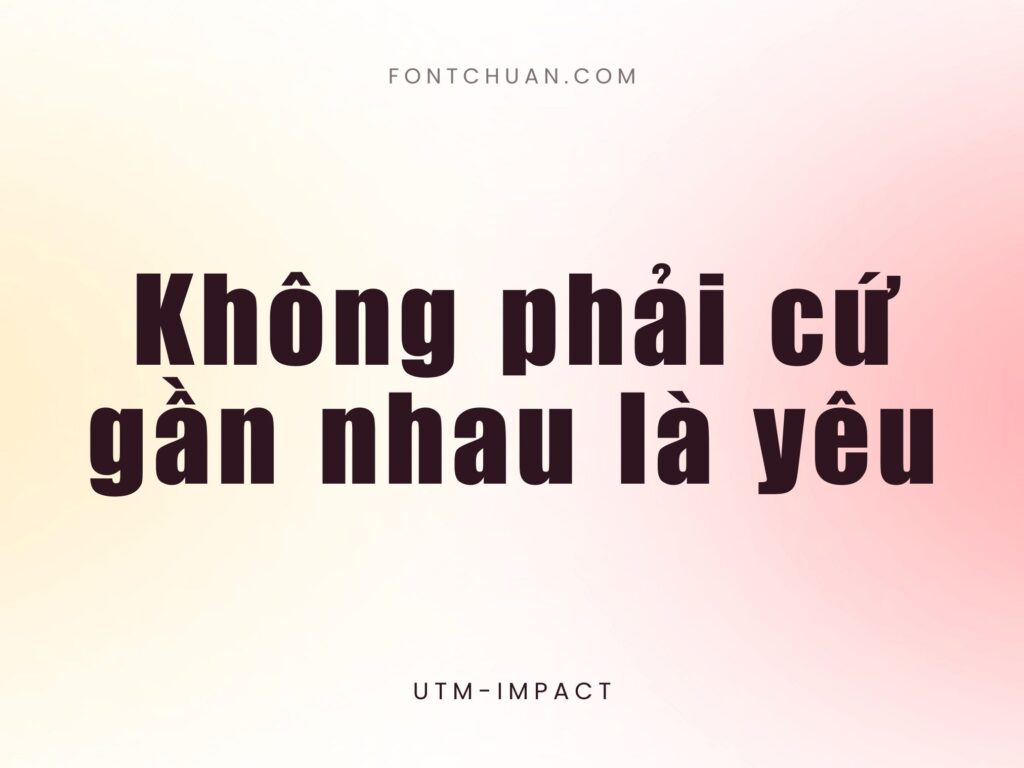
UTM Impact là phiên bản Việt hóa của font chữ Impact, một kiểu chữ sans-serif được thiết kế bởi Geoffrey Lee và phát hành bởi nhà in Stephenson Blake vào năm 1965. Font này nổi bật với các ký tự có đường nét dày, khoảng cách giữa các chữ cái hẹp và chiều cao x lớn, tạo cảm giác mạnh mẽ và thu hút. Phiên bản Việt hóa đã được thực hiện bởi Michael Đinh Kiên, hỗ trợ đầy đủ tiếng Việt cùng hơn 100 ngôn ngữ khác. Đây là một trong những font được cộng đồng thiết kế sưu tầm và chọn lọc nhằm đáp ứng nhu cầu đa dạng trong thiết kế.
UTM Impact có cấu trúc chữ với các nét đậm và khoảng cách hẹp giữa các ký tự, tạo nên sự nổi bật và dễ đọc. Font này phù hợp cho các ứng dụng như thiết kế tiêu đề, logo, biển hiệu và các ấn phẩm in ấn yêu cầu sự mạnh mẽ và ấn tượng. Các ngành nghề như quảng cáo, giáo dục, công nghệ và bất động sản có thể tận dụng UTM Impact để tạo điểm nhấn độc đáo trong thiết kế.